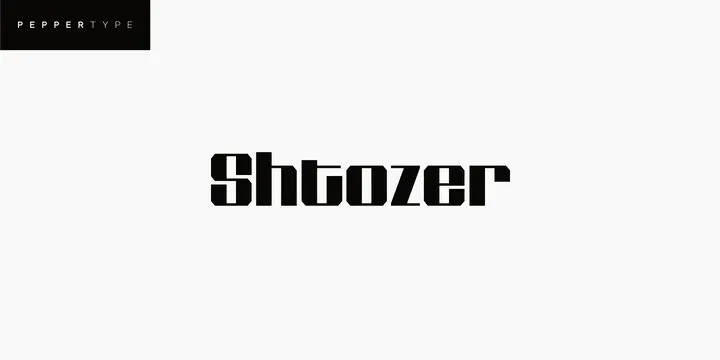
A Shtozer Font Family é uma elegante opção para designers que procuram algo moderno e versátil, criada por Pepper Type. Esse tipo exclusivo não apenas oferece atrações retro inspiradas nos arcos-íris design dos anos 60 e 70, mas também se sobressai com ornamentos do alfabeto cirillico que remetem à arte da Vyaz. Ideal para estilos de exibição, esse tipo multilinguístico é uma verdadeira joia em qualquer projeto. Suas linhas sutilmente contorcidas e detalhes sofisticados não apenas trazem a essência do design retro, mas também proporcionam um toque moderno que mantém seu estilo inovador. Ideal para criações que precisam de destaque, seja para nomes de marca icônicos ou para slogans memoráveis em qualquer idioma – desde o tradicional até os raras vezes usados, a Shtozer Font Family está equipada para todos esses desafios. Esta fonte é uma escolha perfeita para quem busca um tipo de alta qualidade e versatilidade, que se adapta tanto à exibição quanto ao design.